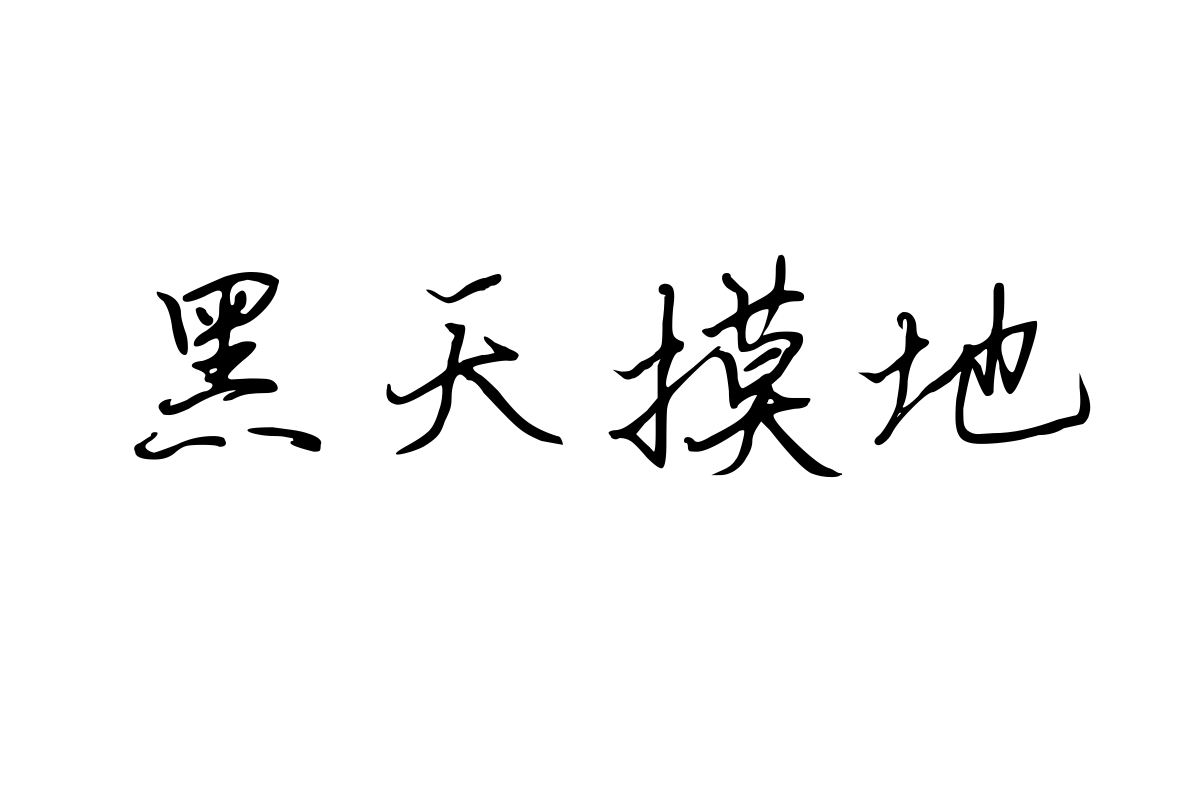
三极钟云毓秀行楷是一套具有独特风格和特点的字体。它由著名书法家王志平先生所创,融合了传统书法与现代审美,形成了一种既有古典韵味又不失现代感的独特字体。
该字体的特点是笔画流畅、结构严谨,每个字都经过精心设计和雕琢,使得整体呈现出一种优美的视觉效果。其笔画粗细适中,线条清晰而有力,给人一种优雅而庄重的感觉。同时,字体中的一些细节部分也经过精心处理,如笔画的连接处、转折处等,使得整个字体更加和谐统一。
此外,三极钟云毓秀行楷还注重字形的变化和节奏感,使得整篇文字富有韵律和动感。无论是在书写还是阅读过程中,都能给读者带来愉悦的感受。
总之,三极钟云毓秀行楷是一种集传统与现代、艺术与实用于一体的优秀字体,适合用于各种场合,如书法创作、设计作品等。